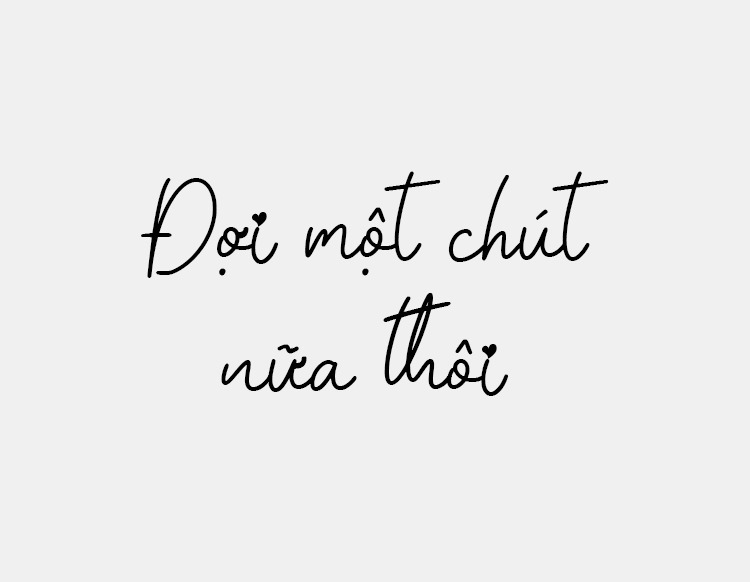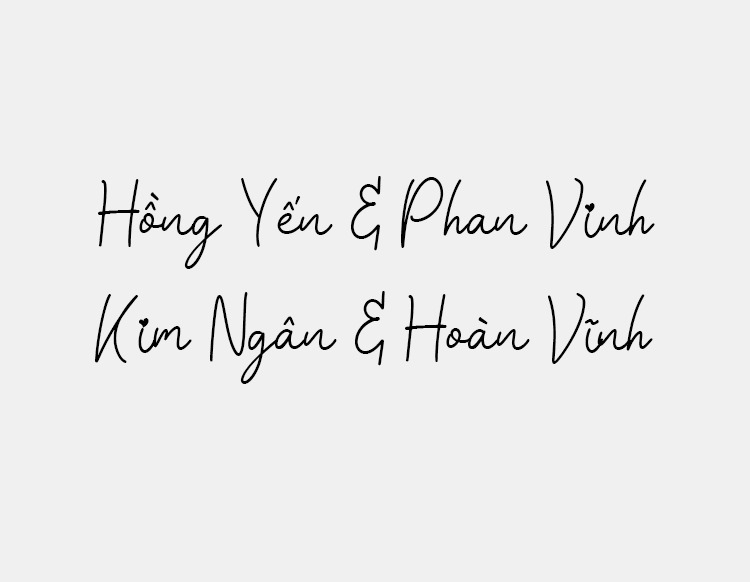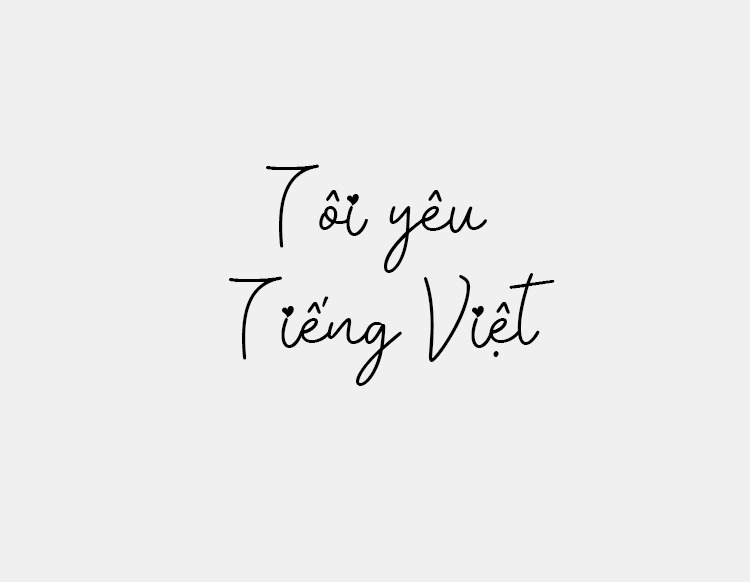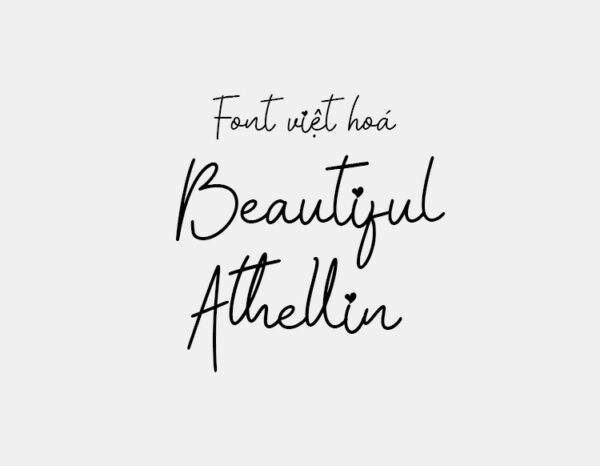
Font việt hoá MJ Beautiful Athellin là font chữ viết tay đẹp và quyến rũ. Phông chữ này có hỗ trợ chữ thường, chữ hoa, chữ ghép, số, dấu câu và đa ngôn ngữ.
Hoàn hảo cho đám cưới, nhiếp ảnh, Giáng sinh, Valentine, lời mời, giấy chứng nhận, sinh nhật, v.v.
Font việt hoá MJ Beautiful Athellin